폰트로 확 바뀌는 시공간! 산돌구름이 추천하는 역사·판타지 장르 폰트 4종
역사/판타지 장르에 딱 어울리는 폰트
역사적 사건이나 과거 시대를 배경으로 하는 영화와 드라마에서는 의상과 소품, 세트 등 여러 미술 장치로 그 시대를 표현하는데요. 소품, 간판, 자막, 포스터에 사용된 글꼴로도 시대상을 재현하는 모습을 볼 수 있죠. 폰트만 바꿔도 시공간 배경이 바뀌는 듯한 느낌을 줄 수 있는데요. 역사/판타지 장르에 어울리는 폰트 4종을 소개합니다.
1. 산돌 / Sandoll 가웨인
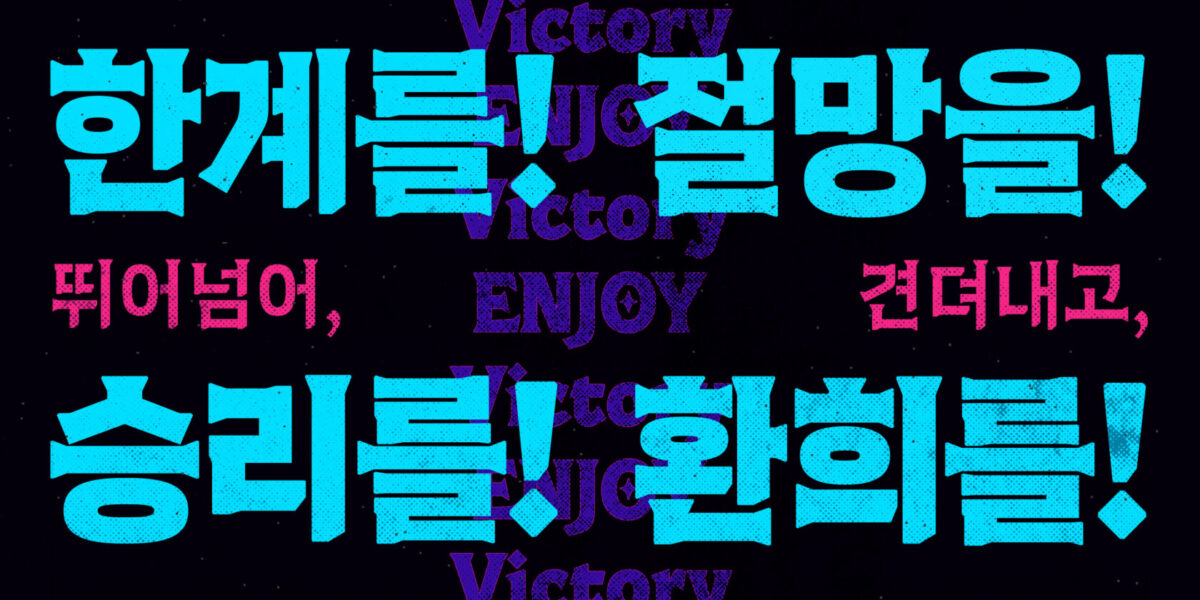
‘Sandoll 가웨인’은 판타지 장르에서 영감을 받아 만들어진 폰트입니다. 폰트명의 주인공인 ‘가웨인’은 아서왕의 기사 중 한 사람인데요. 선하고 용맹한 기사처럼 직선으로 이뤄진 자소와 세리프가 특징적이에요.
또한 ‘Sandoll 가웨인’은 고전적이고 현대적인 인상을 모두 가지고 있어, 시대를 초월해 다양한 분위기를 표현할 수 있도록 만들어졌습니다. 따라서 고전적인 서사시의 표지에도, 판타지스러운 게임 타이틀에도 잘 어울리는 만능 폰트로 추천합니다!
2. 키그타입 / 조각도
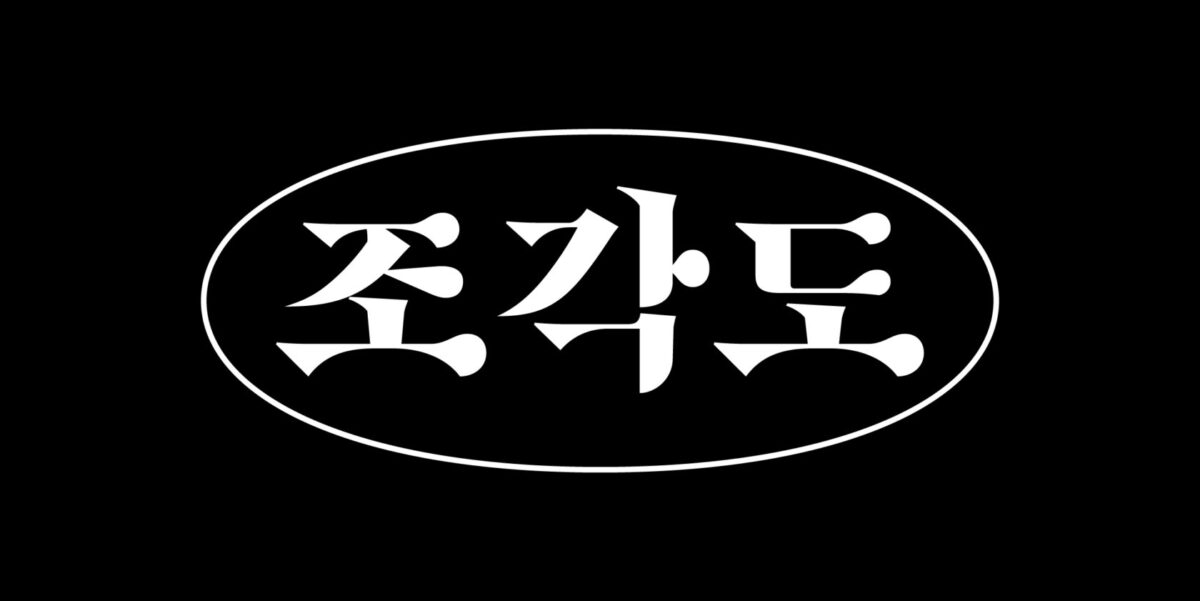
‘조각도’ 는 도검에서 나타나는 강하고 날카로운 인상을 표현한 디스플레이 폰트입니다. ‘ㅈ’의 가로획을 보면 마치 날카로운 칼과 이어진 손잡이와 같은 형태를 볼 수 있는데요. 전통적인 글자 구조에 명확하게 다듬어진 형태로 현대적인 미까지 느껴집니다.
조각도 폰트의 다른 특징 중 하나는 3가지의 도트 스타일(Dot Circle, Dot Square, Dot Triangle)을 지원하는 점인데요. 일반적인 폰트에서는 보기 드문 스타일로 폰트만으로 독특한 그래픽 디자인을 완성할 수 있어요. 디스플레이용으로 제작되어 큰 지면의 영화 포스터나 영상 광고 속에 사용해 보시는 것을 추천합니다.
3. 윤디자인 /Yoon 개항로
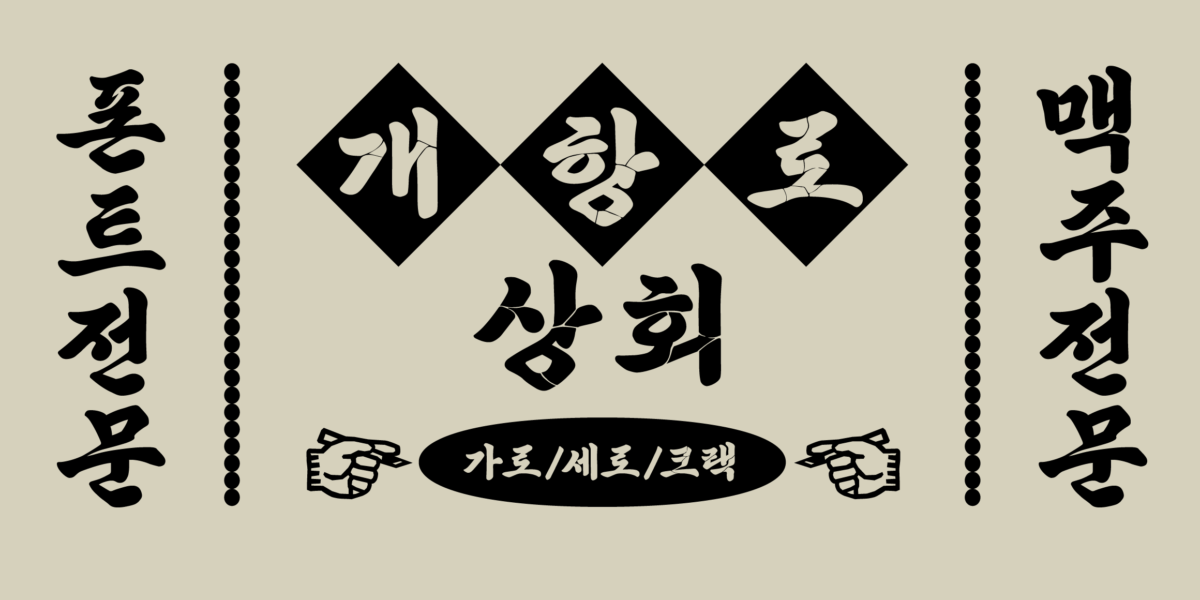
‘Yoon 개항로’ 는 인천 개항로 프로젝트의 협업으로 만들어진 서체로, ‘개항로 맥주’ 로고 타입에서 시작된 컨셉의 폰트입니다. 목간판 글씨를 모본으로 하여 나무를 파고 색을 칠한 글씨에서, 기존의 붓글씨 폰트와는 색다른 인상을 자아내죠.
일반적인 쓰기 방식인 가로 버전과 함께, 세로쓰기를 위한 세로 버전, 목간판의 질감이 느껴지는 크랙 버전까지 지원합니다. 폰트만 봐도 140년의 세월이 느껴지는 힘찬 옛글씨로, 역사적 배경의 간판이나 포스터 디자인에 활용해 보세요.
4. 캐스트 / Rhau
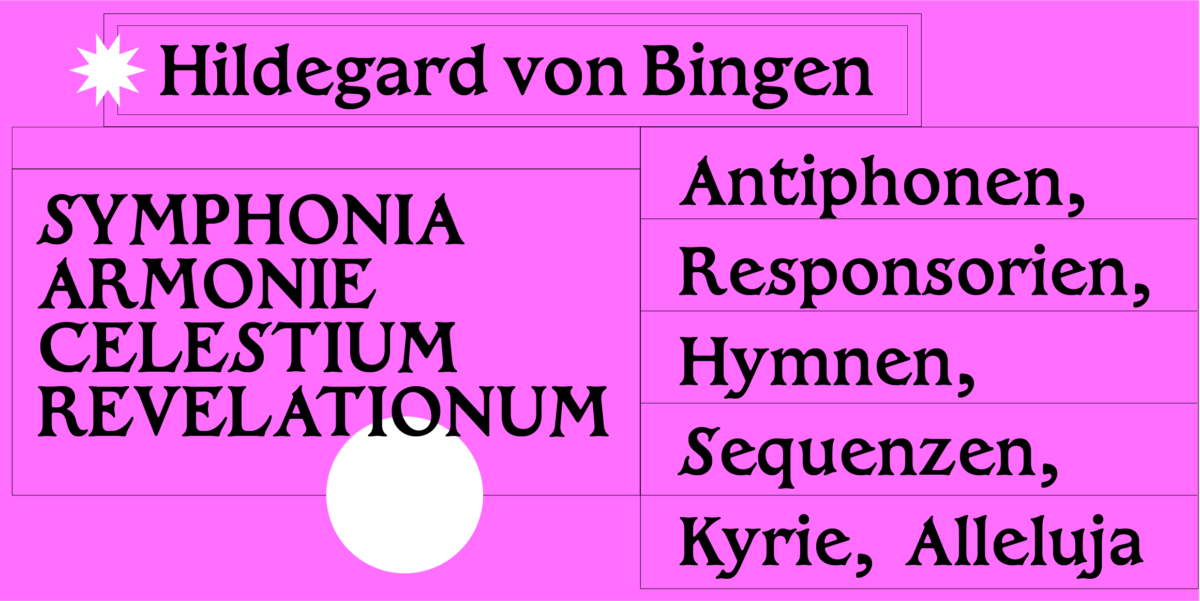
‘Rhau’ 는 목판화의 활자체를 디지털로 부활시킨 폰트로, 거칠고 독특한 질감이 느껴집니다. 단순한 직선이 아니라 미묘한 곡선으로 표현되어 있어 자연스러운 동시에 생동감을 주는데요.
‘S, E ,C’ 와 같은 자소에서 과하게 표현된 세리프는 힘차게 상승하는 에너지까지 느껴지게 하죠. 빛바랜 고대 문헌이나 거대한 비석 위에 새겨진 글자의 모습이 상상되기도 합니다. 판타지 장르의 소품이나 표지 타이틀, 영상 자막 등 다양한 용처의 제목용 폰트로 사용해 보세요!